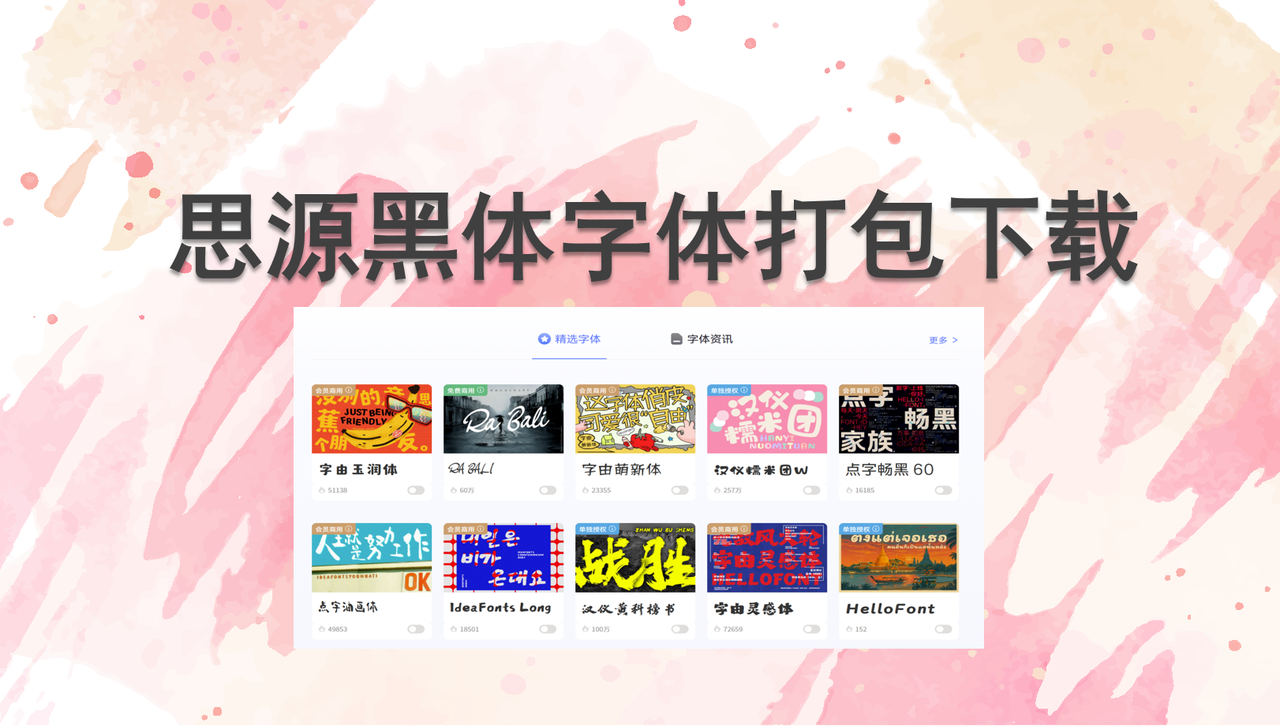
思源黑体作为Adobe和Google联合打造的开源免费字体,凭借多语言支持、字重齐全、适配场景广的优势,成了设计师、开发者乃至普通用户的常用字体。不管是做海报设计、网页排版,还是日常办公排版,用它都能保证清晰美观的视觉效果。但问题来了,网上能下载思源黑体的网站五花八门,不少存在版本残缺、暗藏捆绑软件甚至侵权风险的情况,找个靠谱的下载渠道格外费劲。今天就给大家筛选出4个经过实测的靠谱网站,第一个重点推荐设计师都爱用的字由网,每一个都附简单获取步骤,新手也能轻松搞定。